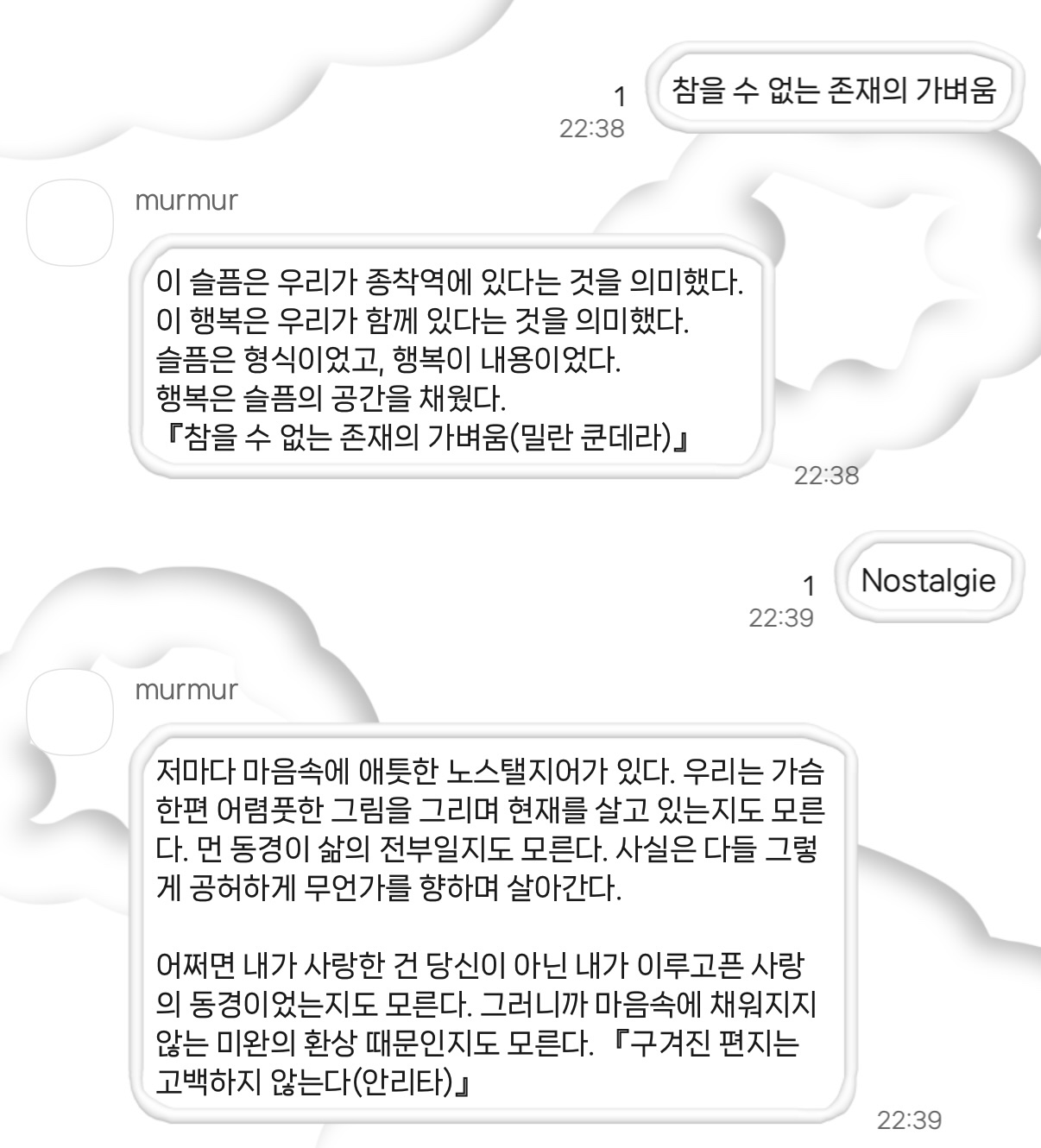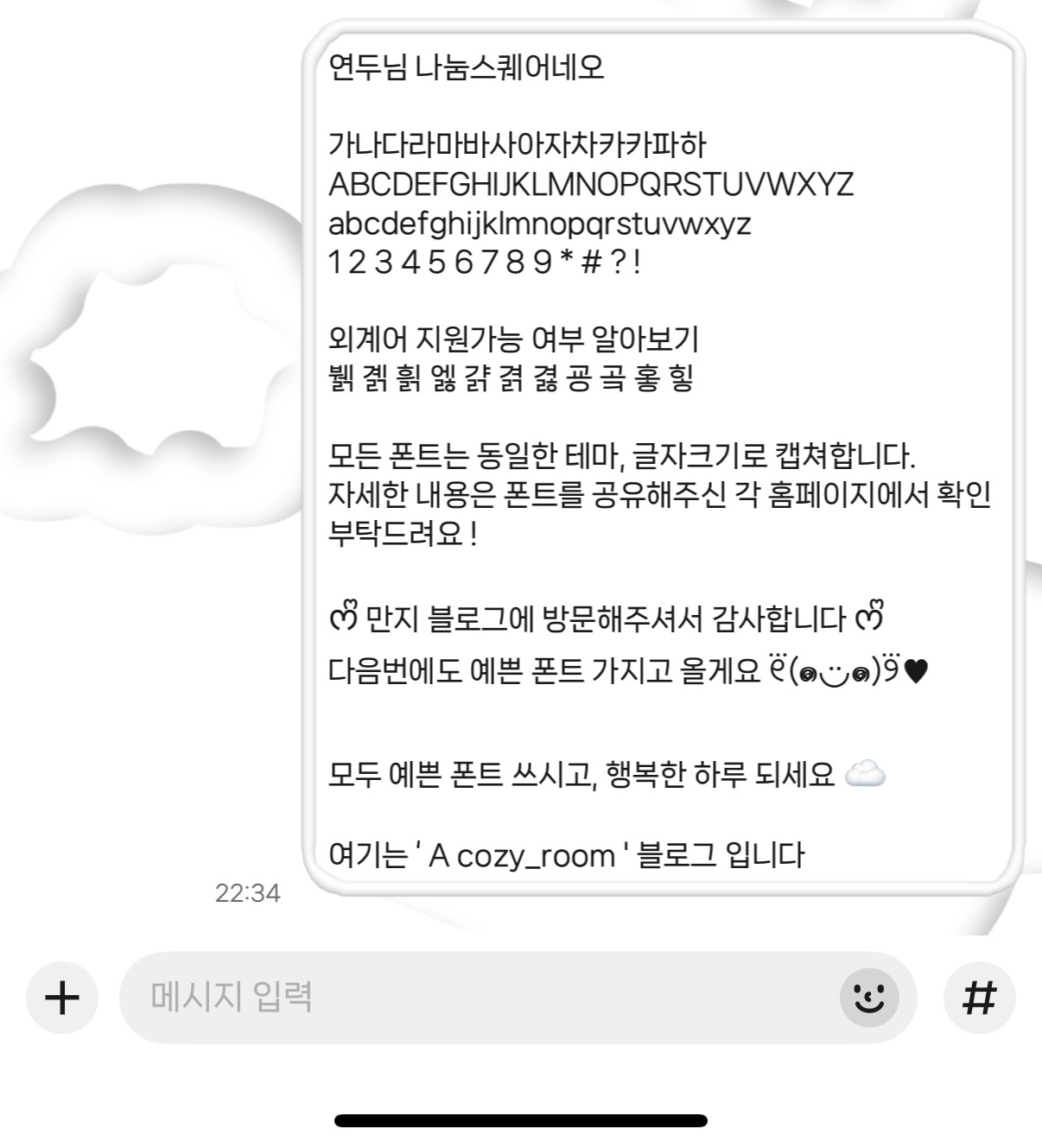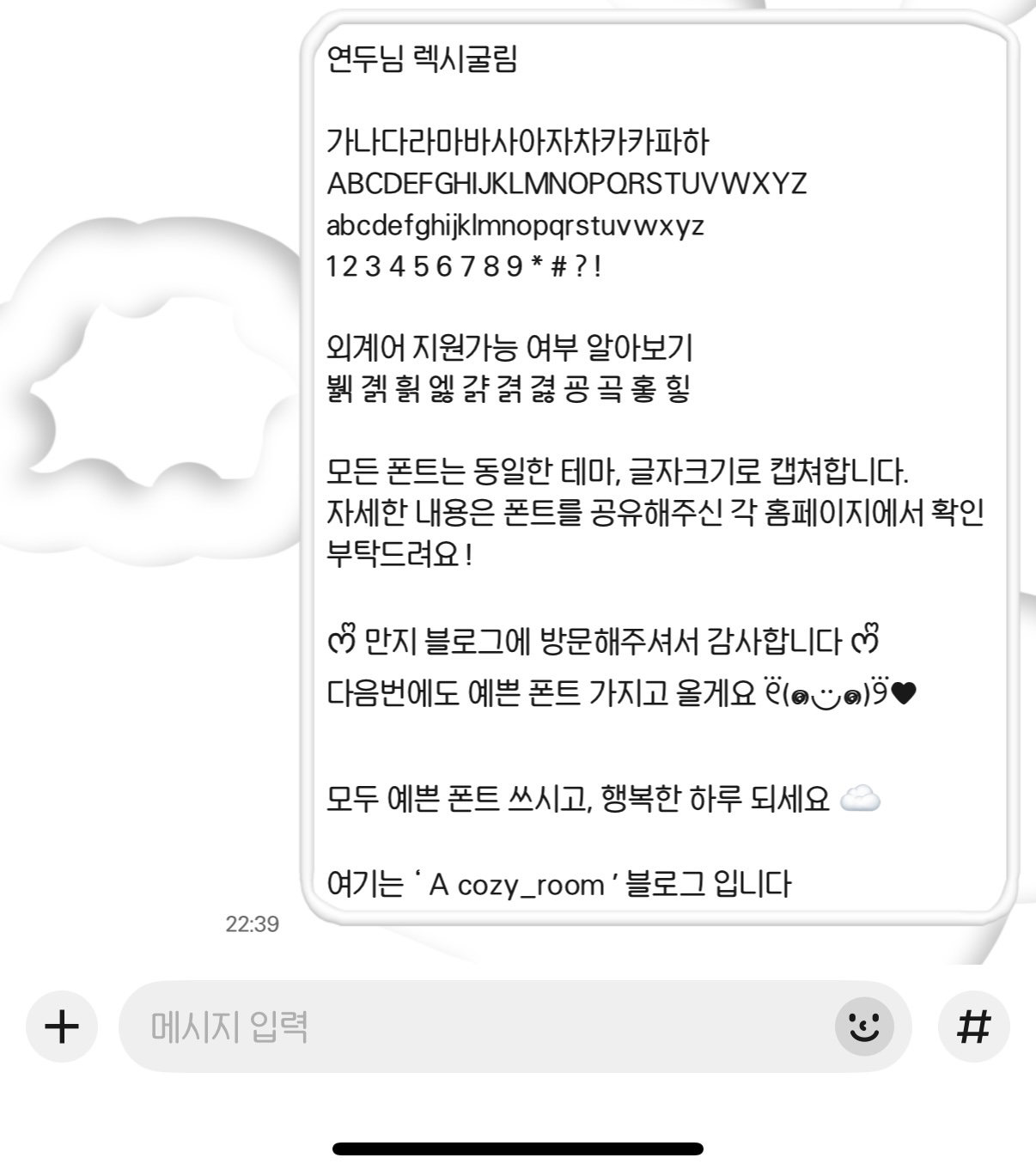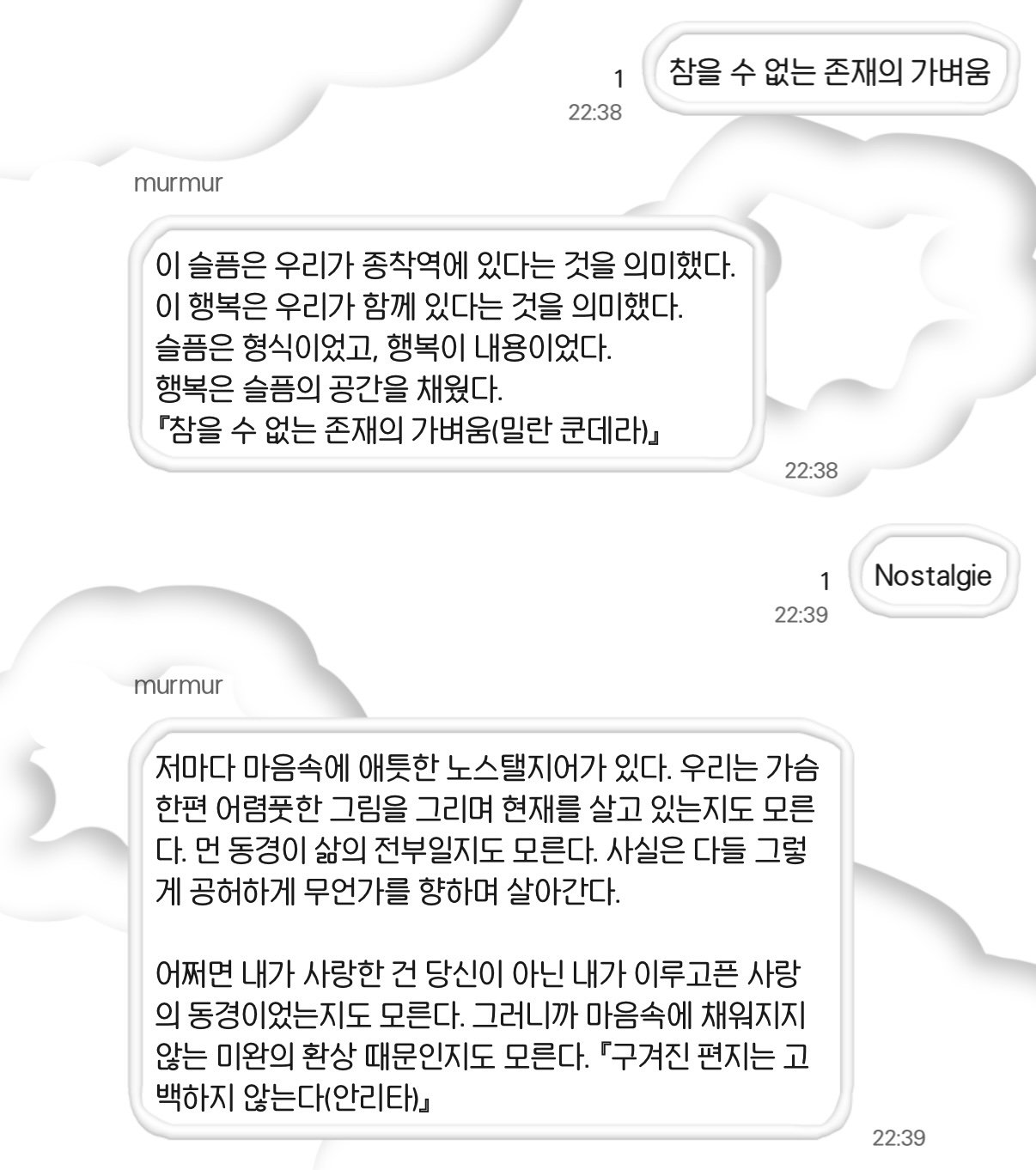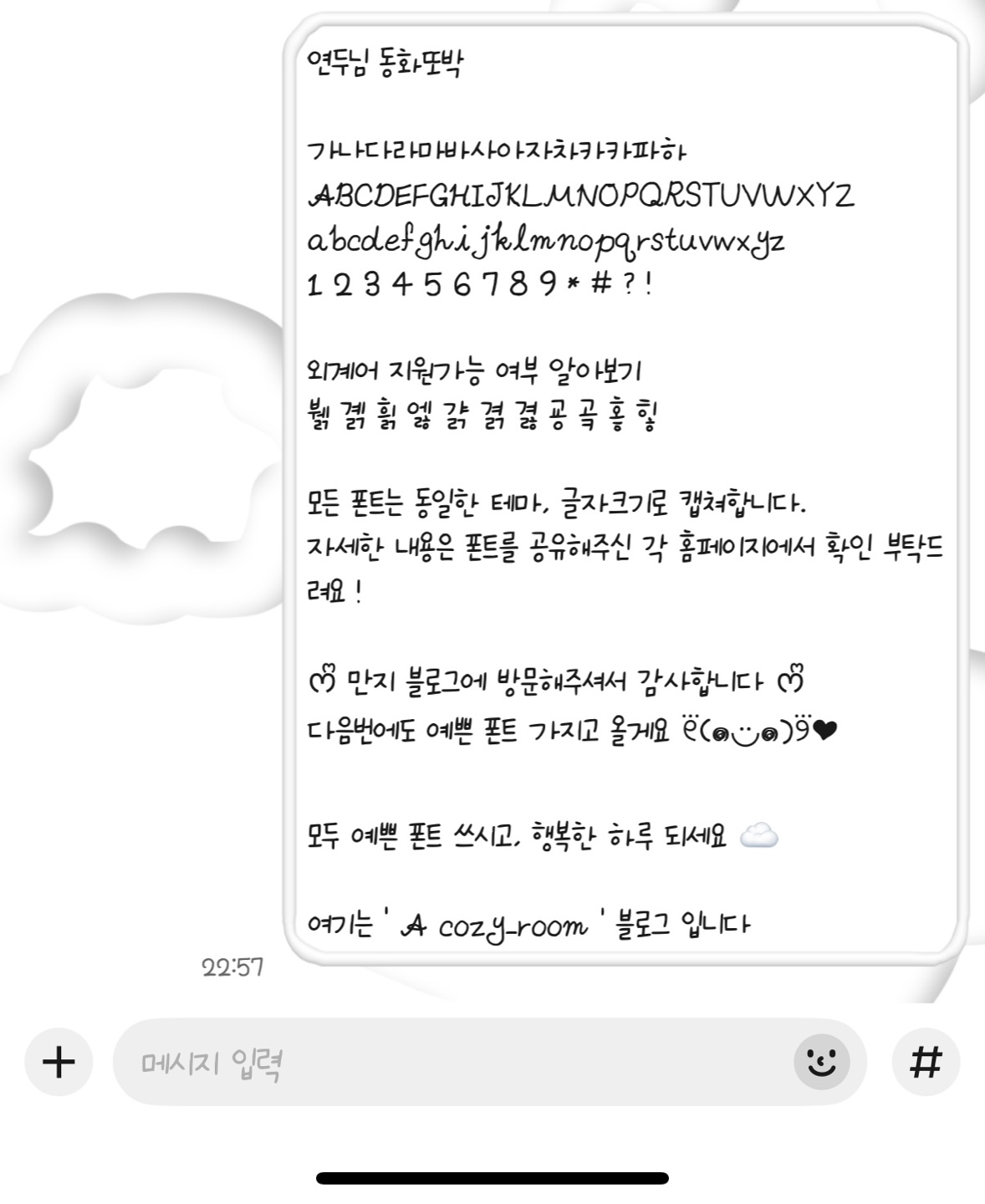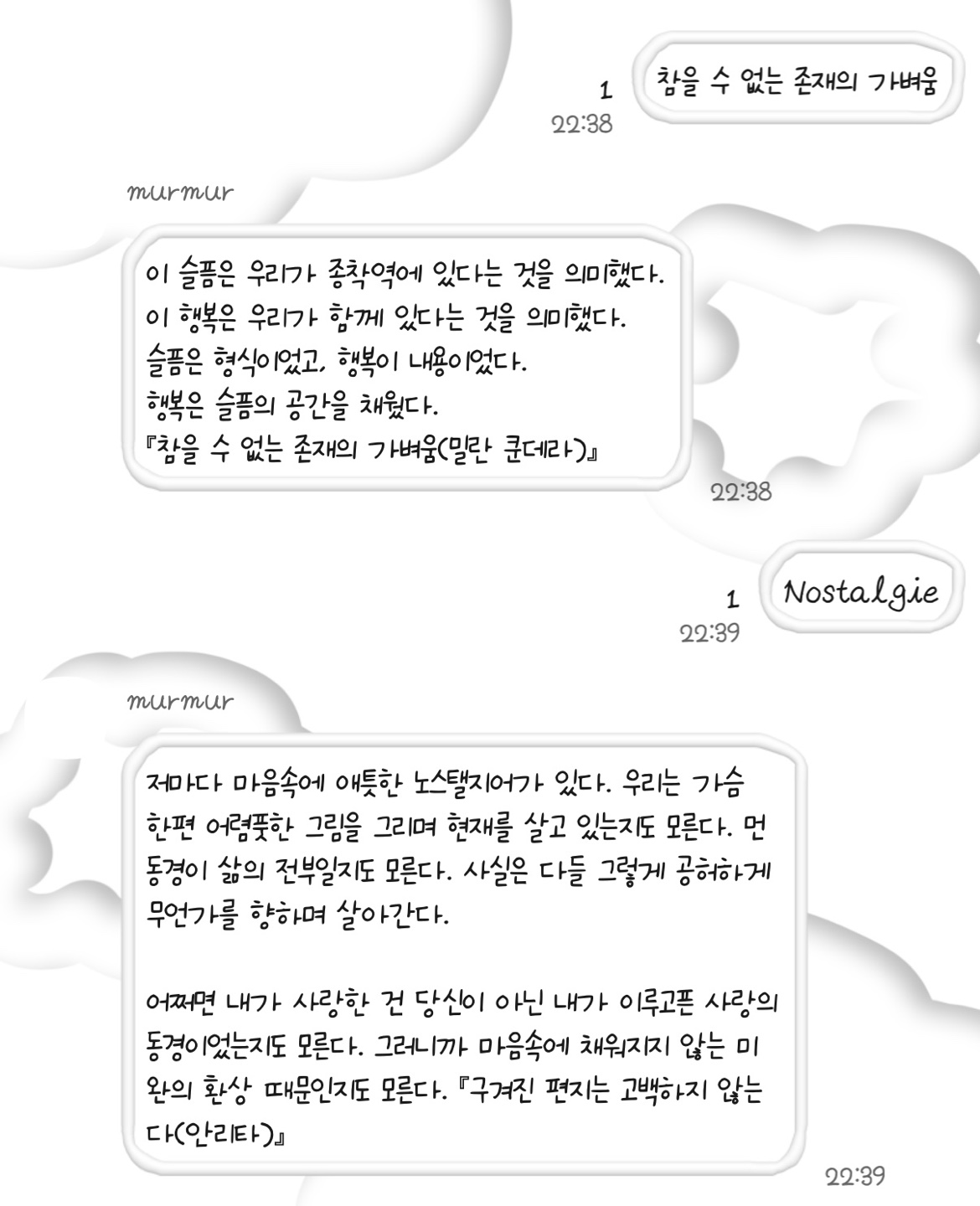
제가 글을 쓰지 않고, 블로그에 오지 않는 동안에도 아이폰 무료폰트 추천글(1탄)이 많은 사랑을 받았더라구요.
1년 반 동안 수 많은 폰트를 써온 폰트러버로서 당장 제 아이폰에 저장되어 있는 폰트 12개 가져왔습니다 !
이번 글에서는 유료폰트는 제외하고 무료폰트만 추천할게요.
1. 연두님 나눔스퀘어네오
주인장 최애폰트입니다 ' _ ' 🖤
이 폰트는 정말 안질리는 폰트로 1년 내내 쓰기 좋아요.
다른 폰트 쓰다가 질릴 때 무조건 이 폰트로 돌아오신다고 장담합니다 !
2. 연두님 렉시굴림
깔끔한 폰트예요, 가독성이 정말 좋고 질리지 않아요
나눔스퀘어만큼 안질리고 오래쓸 수 있는 폰트랍니다.
3. 연두님 동화또박
앞에 두 폰트와 달리 손글씨 느낌이 많이 나는 폰트예요 !
약간은 기울어진 폰트가 더 귀여운 느낌을 준답니다
4. 온글잎 데몽고딕
온글잎 데몽고딕인데요,
고딕느낌이 나지만 동그랗게 처리되어 있어 손글씨 폰트느낌이 많이나요.
가독성도 좋고 질리지 않으면서도 귀여운 폰트예요
5. 온글잎 우주먼지
귀여우면서도 얇기도 딱 맘에 들었던 폰트예요
손글씨 느낌의 폰트를 찾는다면 이 몽글한 폰트가 포인트가 될 것 같아요
6. 온글잎 호롱포롱체
인스타에 호롱포롱툰 아시나요 ?
그 작가님이 만드신 호롱포롱체예요 ~
귀여운 손글씨 폰트이면서도 약간은 볼드해서 가독성도 좋아요
7. 온글잎 콘콘체
콘콘체는 그런날 쓰기 좋은 폰트예요,
뭔가 너무 고딕스러운 딱딱한 느낌은 싫은데
가독성은 좋은 폰트쓰고 싶은 날이요
8. 온글잎 윤슬체
조금 더 세로로 긴 폰트인 윤슬체.
부러우면서도 흘리듯 쓴 'ㄹ' 이 포인트예요
9. 온글잎 씽아툰체
씽아툰체는 유료폰트 느낌이 많이 나는 듯한 기분이예요.
크기는 다른폰트에 비해 약간 작은 편이라
카톡 사용 시 3으로 두고 사용한답니다.
10. 온글잎 하루나눔
오늘 소개하는 폰트중에 가장 동글동글 귀여운 하루나눔체,
다른 폰트에 비해 크기는 조금 작아서 캡쳐 시 크기 4로 적용했어요
하지만 한번 빠지면 당분간은 이 폰트만 쓰게 될 거예요.
11. 온글잎 몽몽데이즈몽글동심체
귀여운 구름딩벳이 숨어있는 몽몽데이즈몽글동심체
오늘 소개하는 폰트 중 가장 이름이 긴 폰트예요.
이 폰트도 크기가 조금 작아서 캡쳐 시 4로 설정해두었답니다.
12. 오뮤 다예쁨체
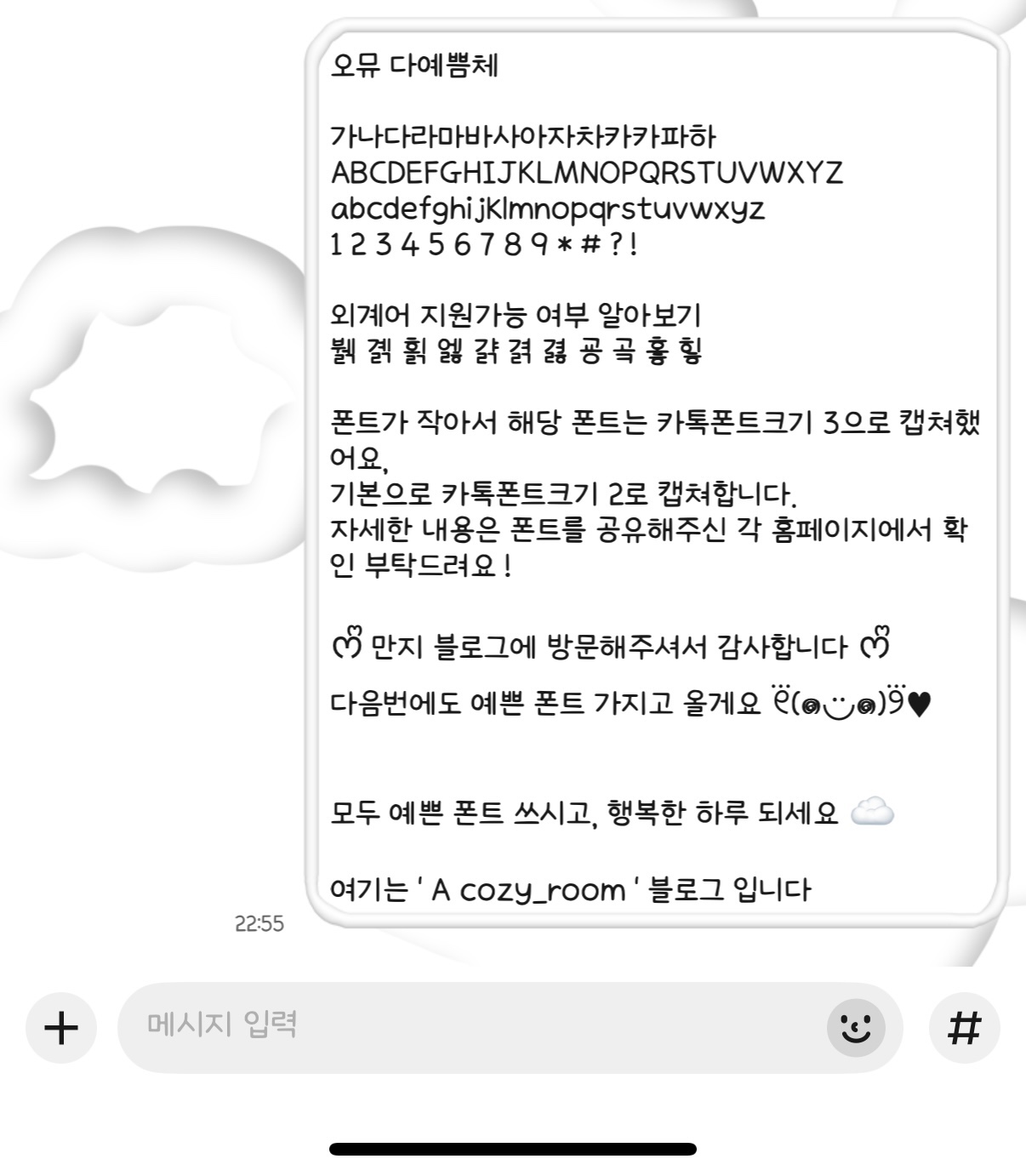
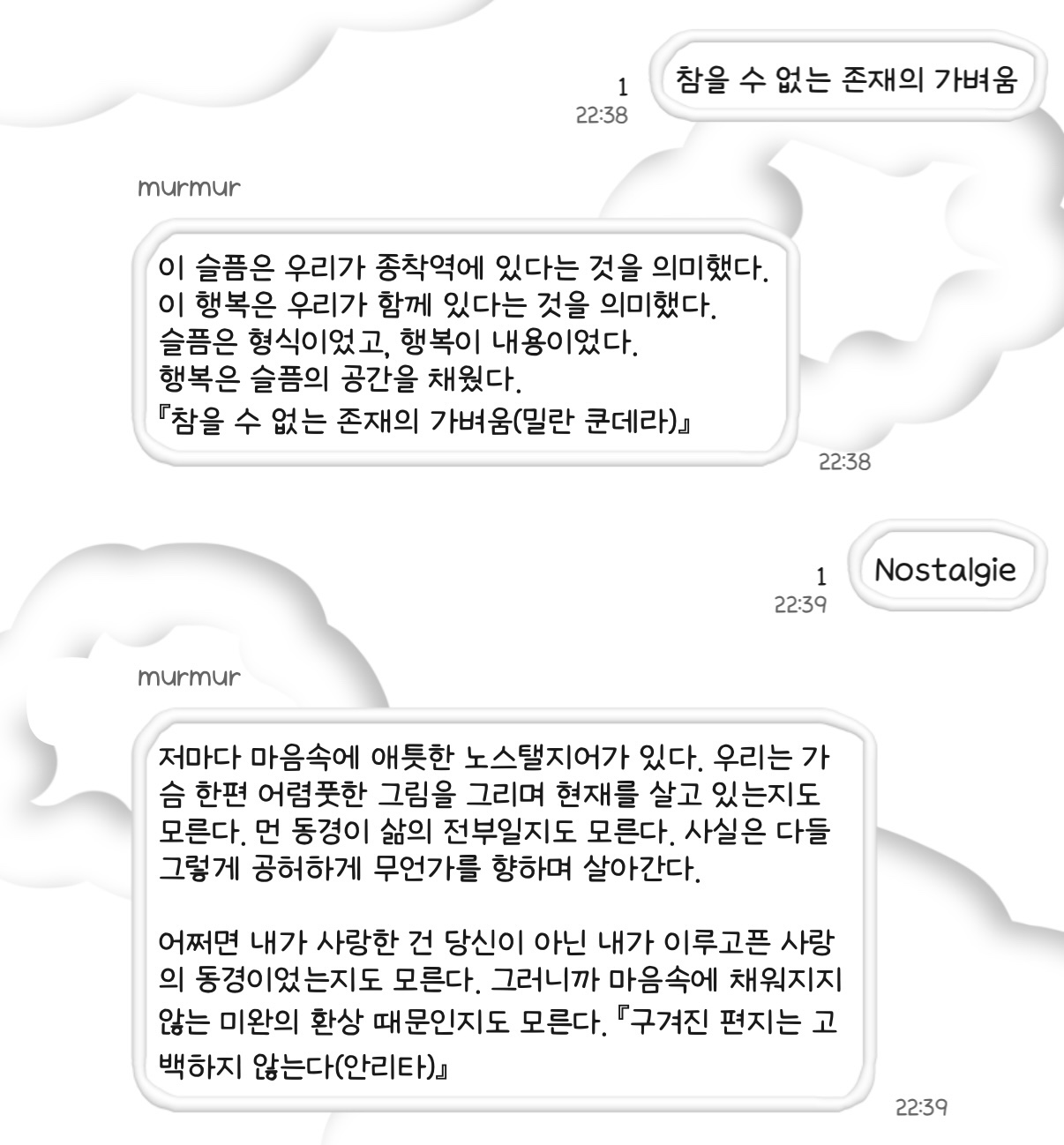
오늘의 마지막폰트, 정사각 네모반듯한 오뮤 다예쁨체랍니다.
다예쁨체는 폰트가 약간 작아서 3으로 두고 사용을 했어요.
직사각으로 반듯한 폰트와는 다른느낌의 정갈함이 돋보여요 !